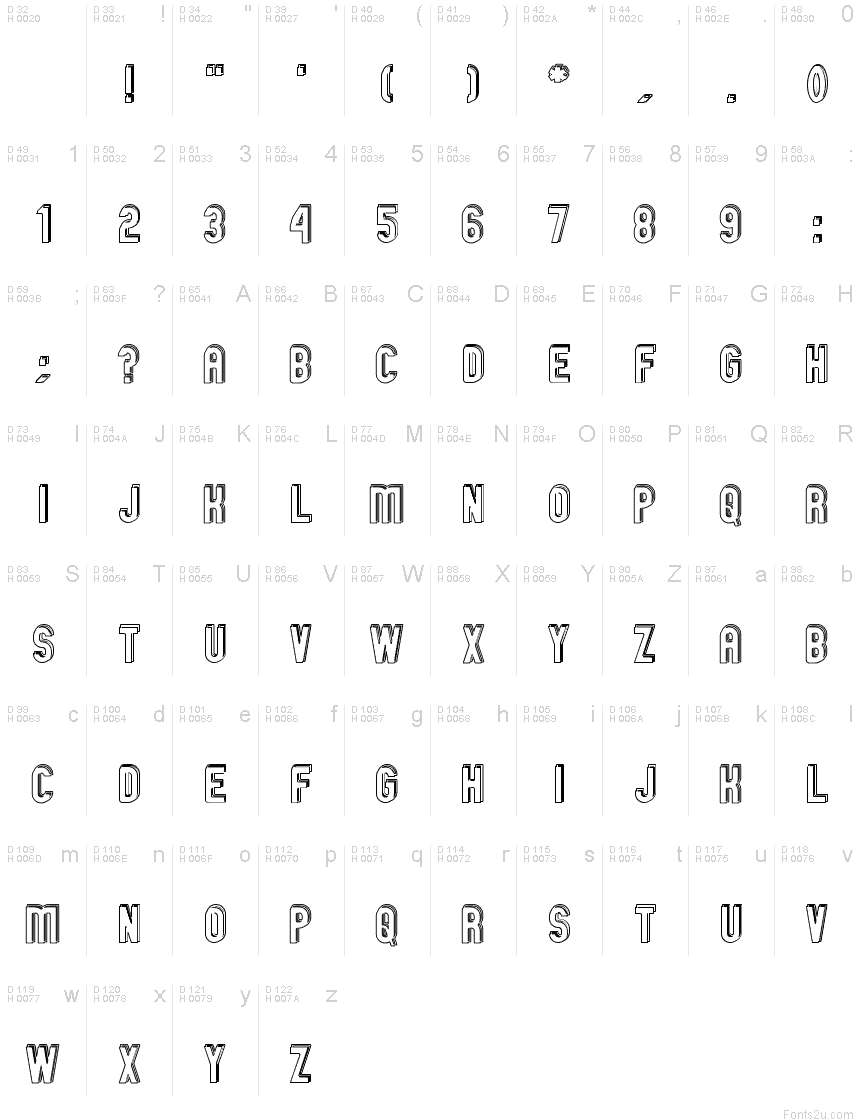
GM Exp Offset Doubleoutline
GM Exp Offset Doubleoutline od G.M. to darmowy krój pisma 3D z efektem obrysu, który wygląda, jakby został narysowany precyzyjnym pisakiem technicznym, a następnie przesunięty w celu uzyskania pomysłowego podwójnego konturu. Wąskie wewnętrzne kształty i przesunięta zewnętrzna warstwa nadają każdej literze wyraźny, mechaniczny blask, przypominający liternictwo z dawnych projektów technicznych czy tłoczone szyldy. Linie są czyste, ale nie zimne, zachowując naturalną, ludzką nieregularność, dzięki czemu nie wydają się sterylne.
Dzięki GM Exp Offset Doubleoutline nagłówki natychmiast zyskują głębię i dynamikę, bez konieczności stosowania dodatkowych efektów czy warstw. Ten darmowy font świetnie sprawdza się na plakatach w stylu retro, ulotkach, opakowaniach, w tytułach gier, oznakowaniach czy wyrazistych logotypach, w których chcesz połączyć mocny efekt z nutą nostalgii. Spróbuj połączyć go z prostym krojem bezszeryfowym w tekście głównym i stosuj GM Exp Offset Doubleoutline w dużym rozmiarze, aby skomplikowane podwójne obrysy pozostały wyraźne i czytelne.